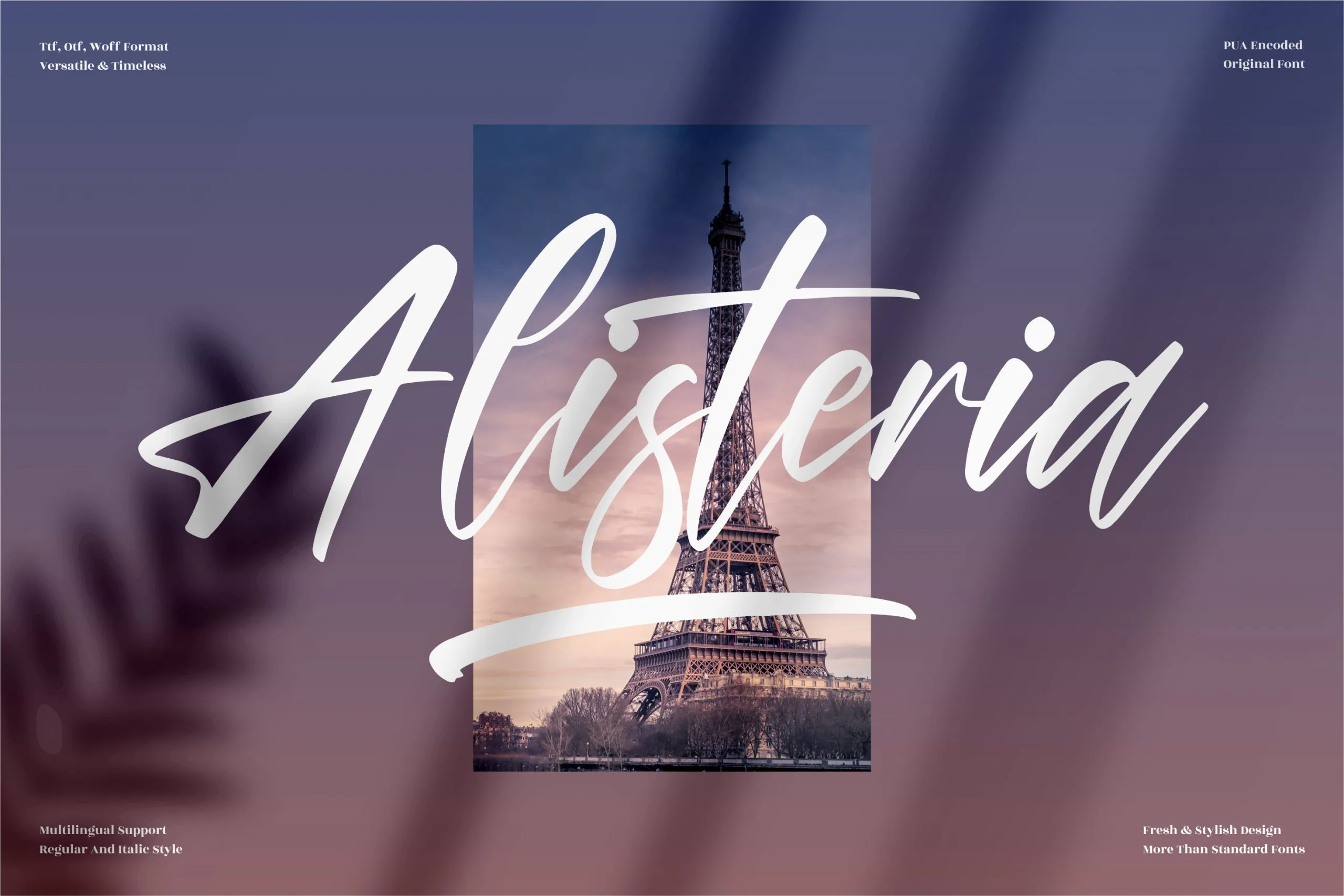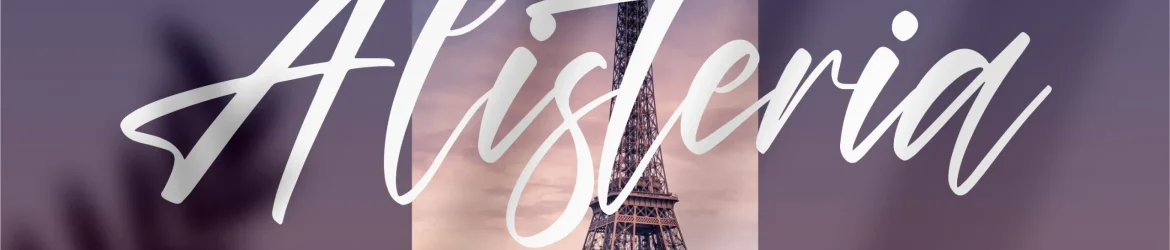
Alisteria Font é uma elegante e sofisticada fonte criada para projetos que exigem premiumza e sabor autêntico. Seja você uma designer ou artista, essa fonte será perfeita para dar um toque único aos seus trabalhos de arte digital, seja isso logos icônicos para marcas, criações de embalagens de produtos e caixas de papelão personalizadas, até mugs exclusivos. Alisteria foi projetada para se misturar com outros tipos, criando texturas que vão desde os mais delicados nomes em cartões de visita até design alegres de capa de livro ou até mesmo um impresso especial para sua próxima festa. Seja qual for o seu projeto, seja uma lembrança de presentear alguém com mala personalizada ou adicionar algo diferenciado ao teu álbum de fotos, Alisteria Font é sua fonte perfeita para dar aquele toque premium e autêntico aos seus projetos.